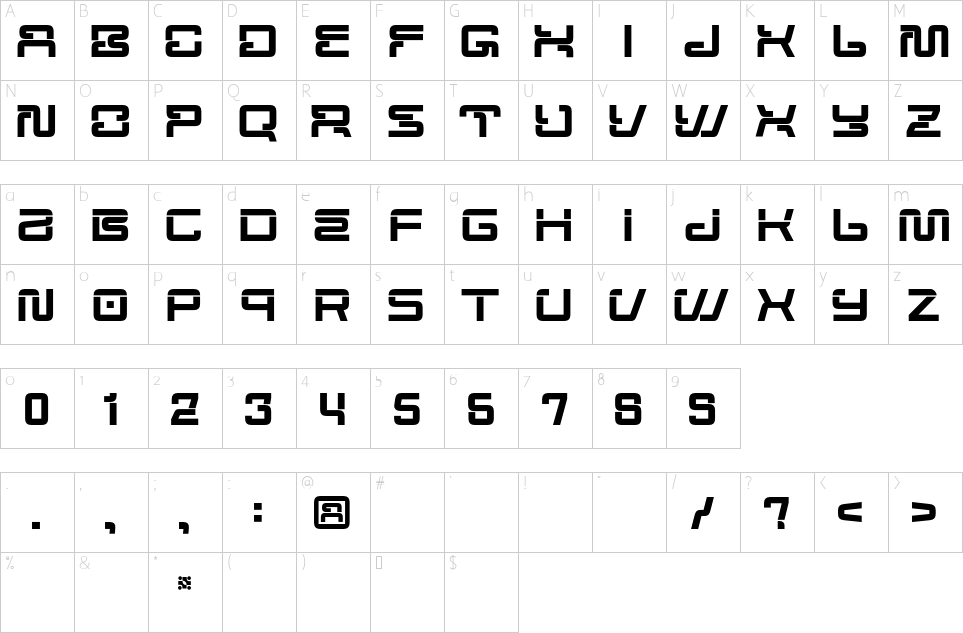
Aqui está uma descrição em português do Brasil, envolvente e natural, para a página de download da fonte ‘Mega Binory Font | 1001 Free Fonts’: A Mega Binory é uma fonte minimalista e sofisticada, ideal para projetos gráficos modernos. Ela foi criada pela Afkari Studio e está disponível gratuitamente para download para sistemas Windows e Mac. Suas formas geométricas e linhas retas criam um efeito clean e contemporâneo, perfeito para textos de aplicativos digitais ou websites. A Afkari Studio oferece uma vasta variedade de fontes gratuitas em seu catálogo, tornando-a uma ótima escolha para profissionais e amantes do design. Com essa fonte, você pode adicionar um toque único e moderno a qualquer projeto, sem precisar gastar nada. Não deixe de baixar sua cópia agora e experimentar os benefícios da fonte Mega Binory.